「いとをかし!和風デザインフォント・筆文字集」の気になる中身
AFSリモーネ
やわらかい雰囲気で読みやすい「AFSリモーネ」。ウェイトも2種類あり、用途に合わせて選べます。
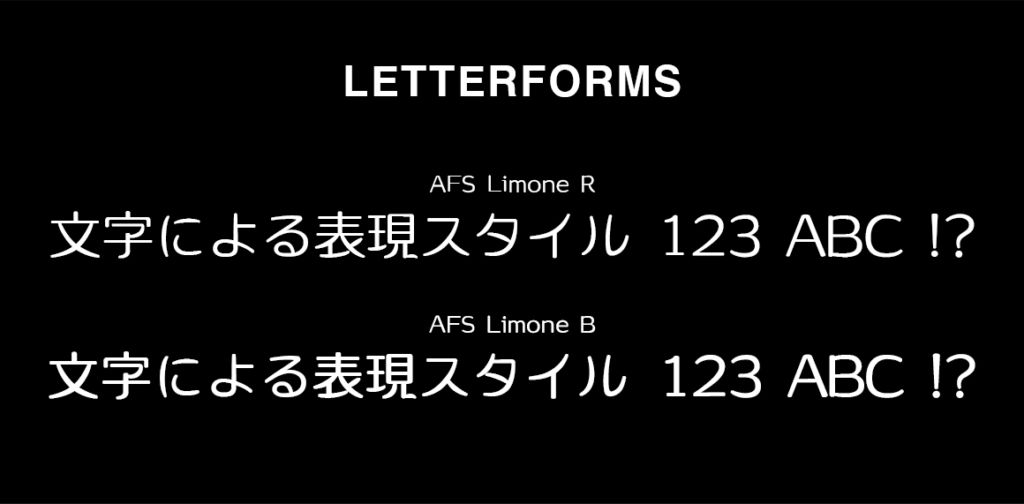
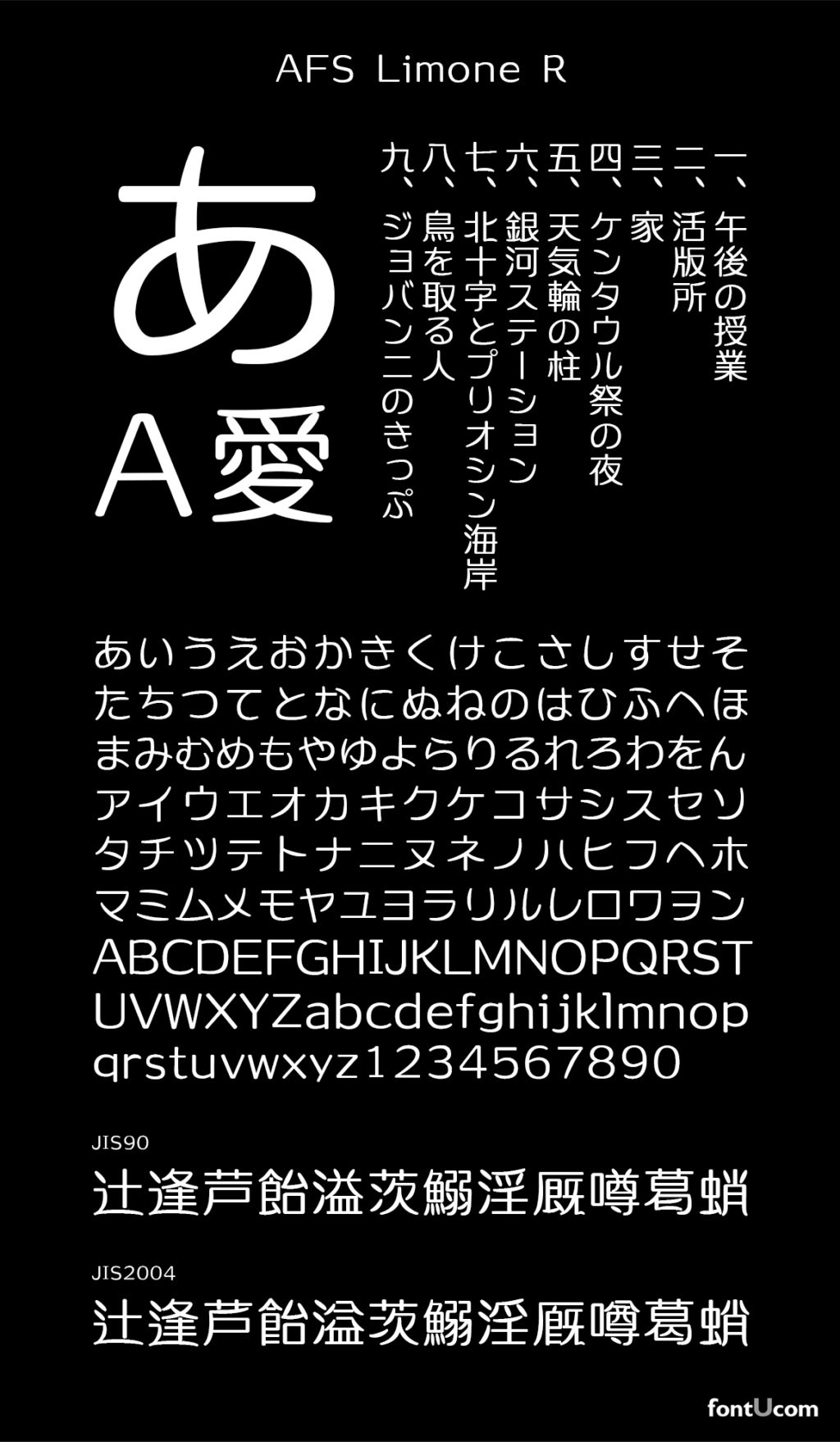
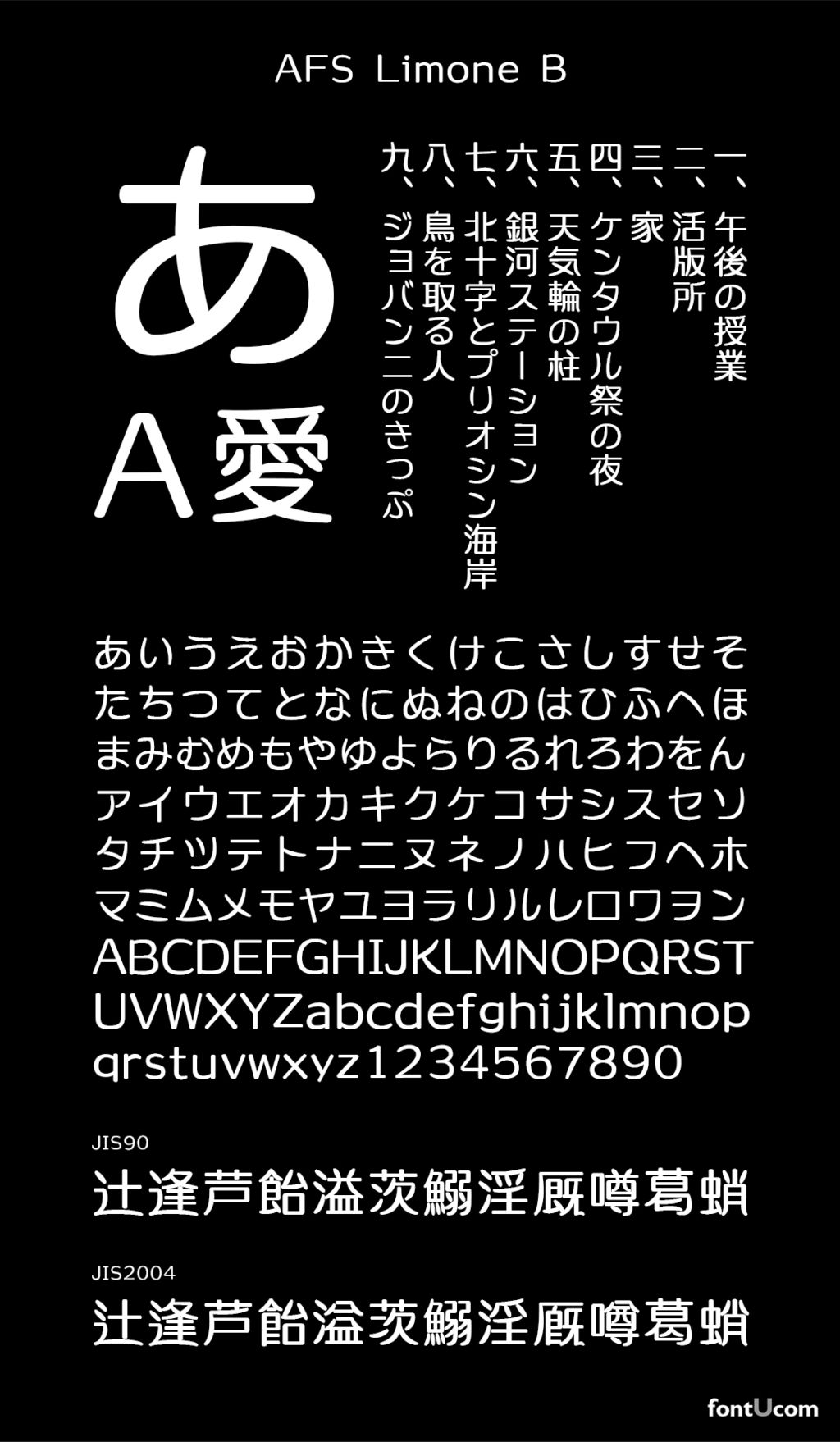
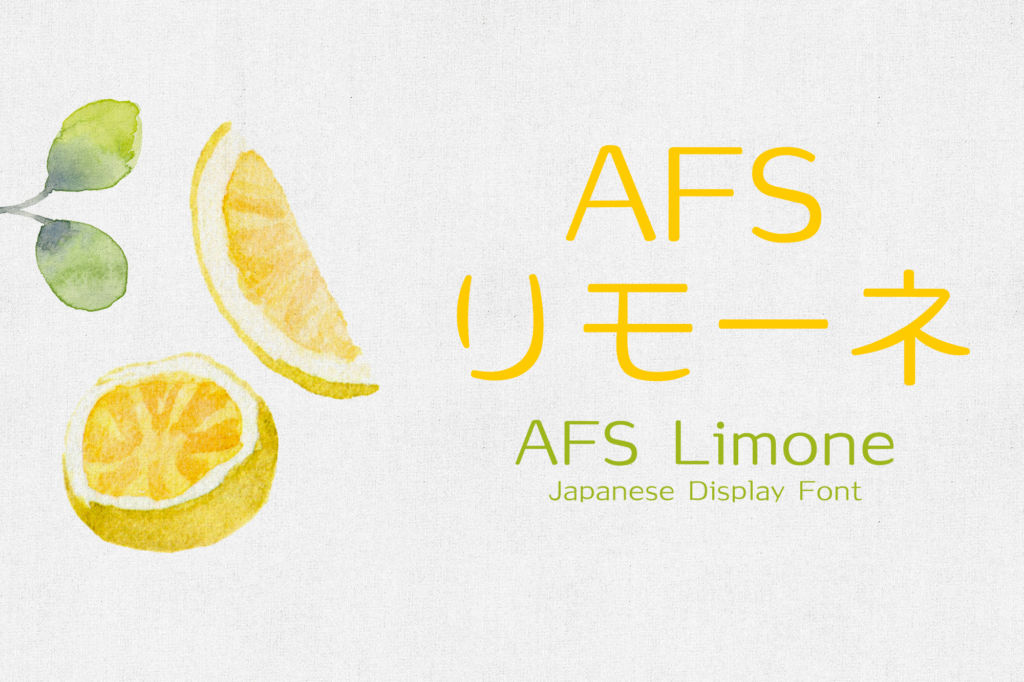
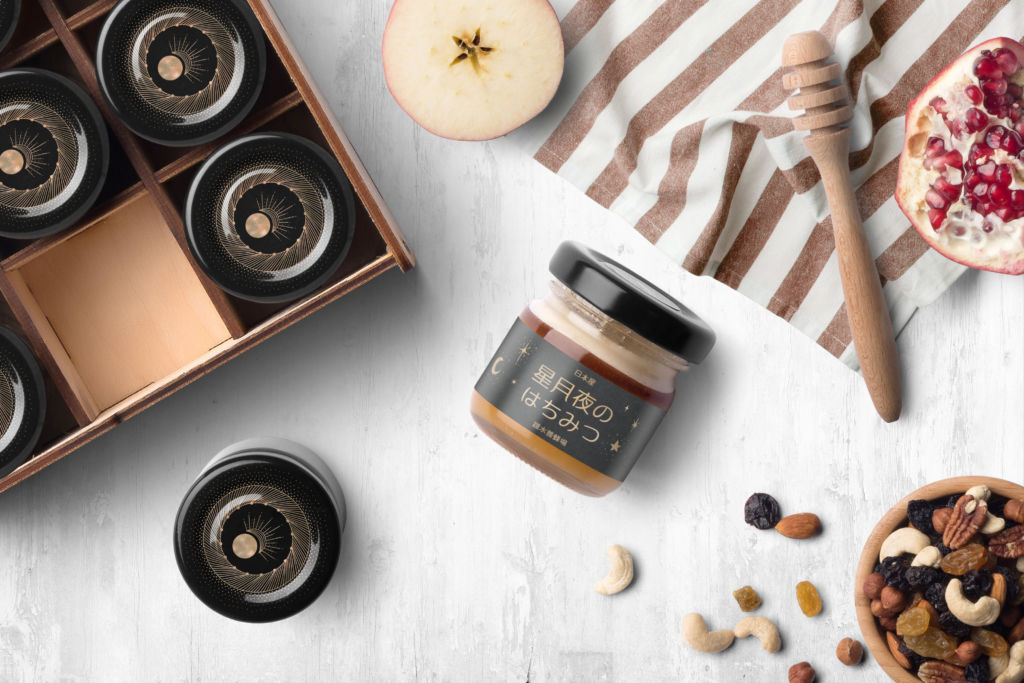
AFSテンドゥ
篆書体ベースのデザインフォント「AFSテンドゥ」。レトロモダンな印象でロゴやラベルのデザインにぴったりです。
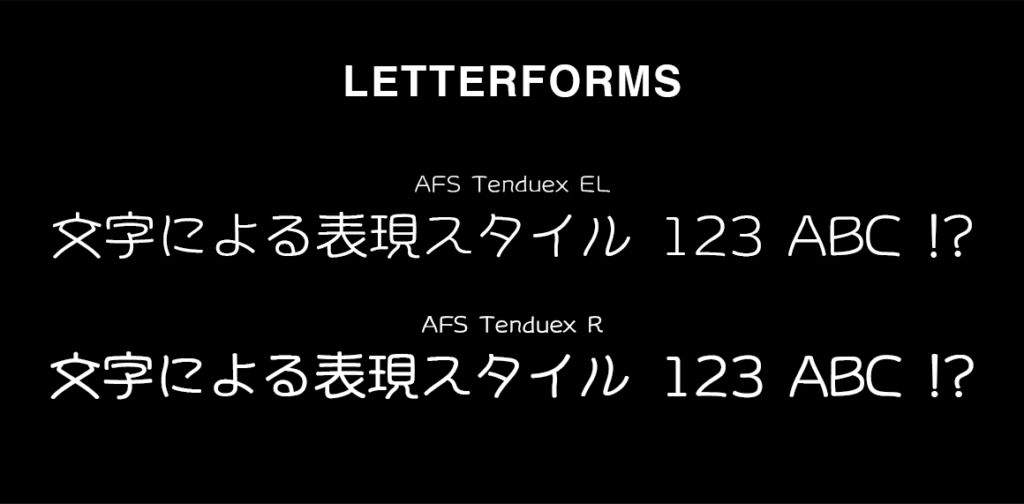
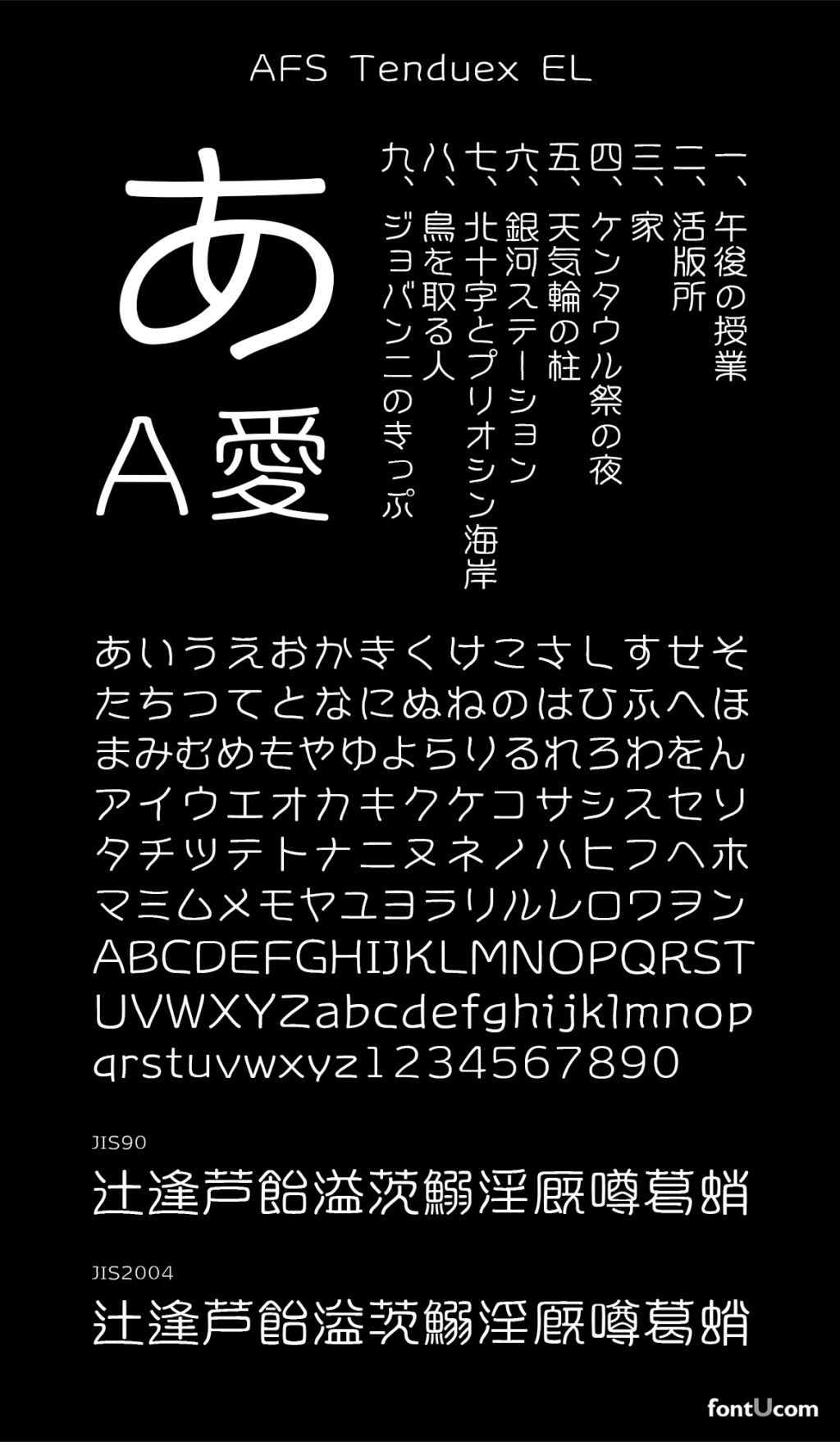
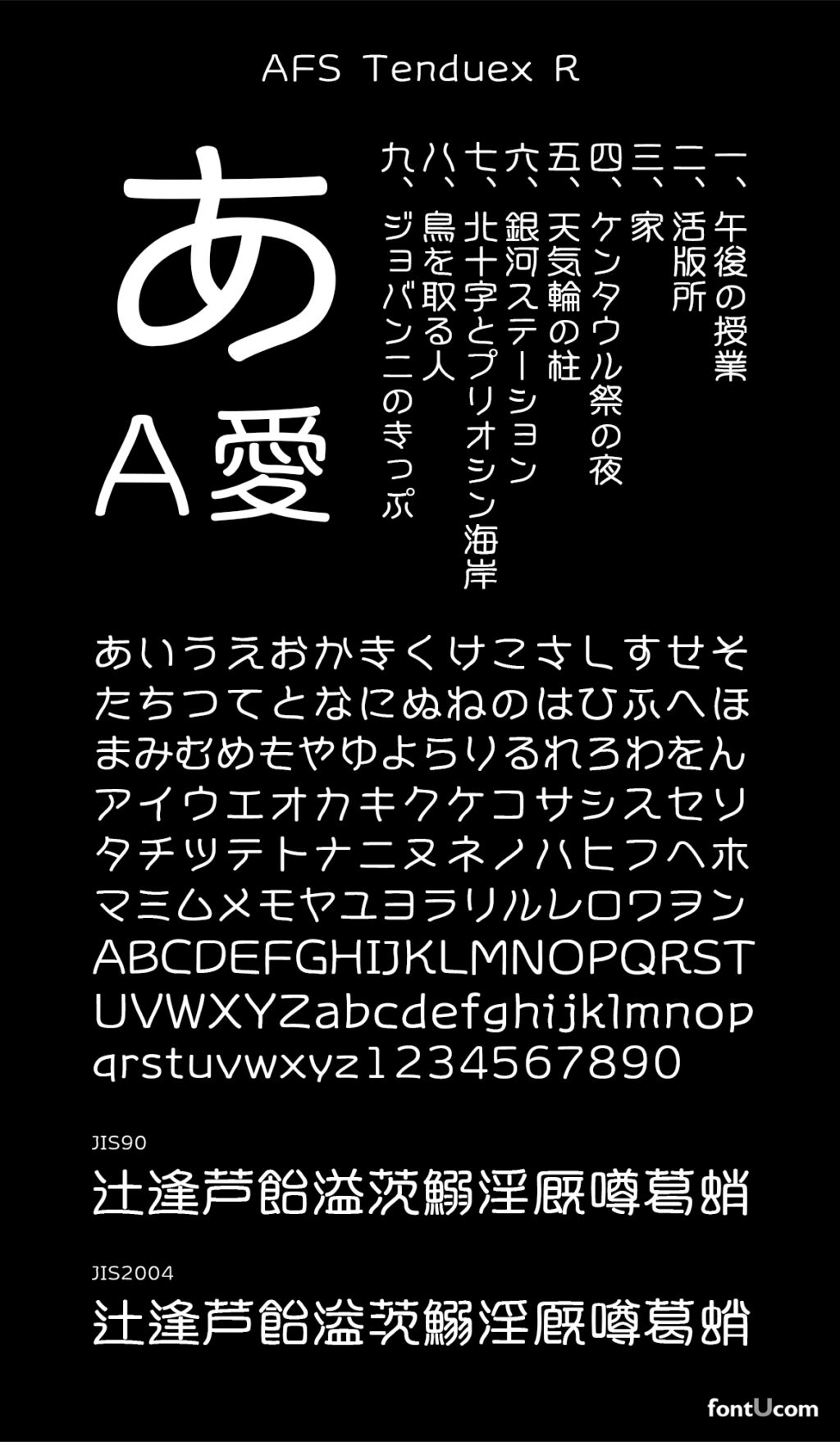
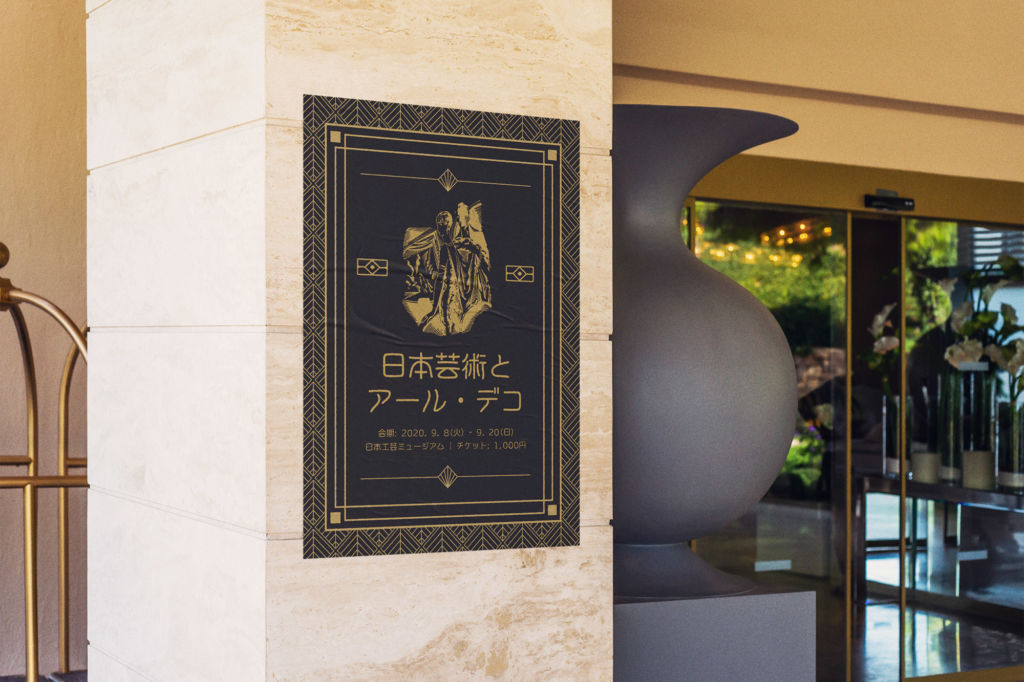
AFSフローラ
横太丸ゴシック体と篆書を組み合わせたブレンド書体「AFSフローラ」。ボディの太さのメリハリが特徴です。
AFSオリーブ
メイリオデザイナー鈴木竹治氏作のデザインフォント「AFS オリーブ」。軽やかな雰囲気でSNSの投稿などにも使えます。
鈴木竹治氏直筆筆文字ベクター集
年賀状のデザインに使いたい、筆文字のベクター素材を計284点収録。「Happy New Year」や、同じ文言の縦組み版と横組み版もあり、デザインによって好きなデータが選べます。